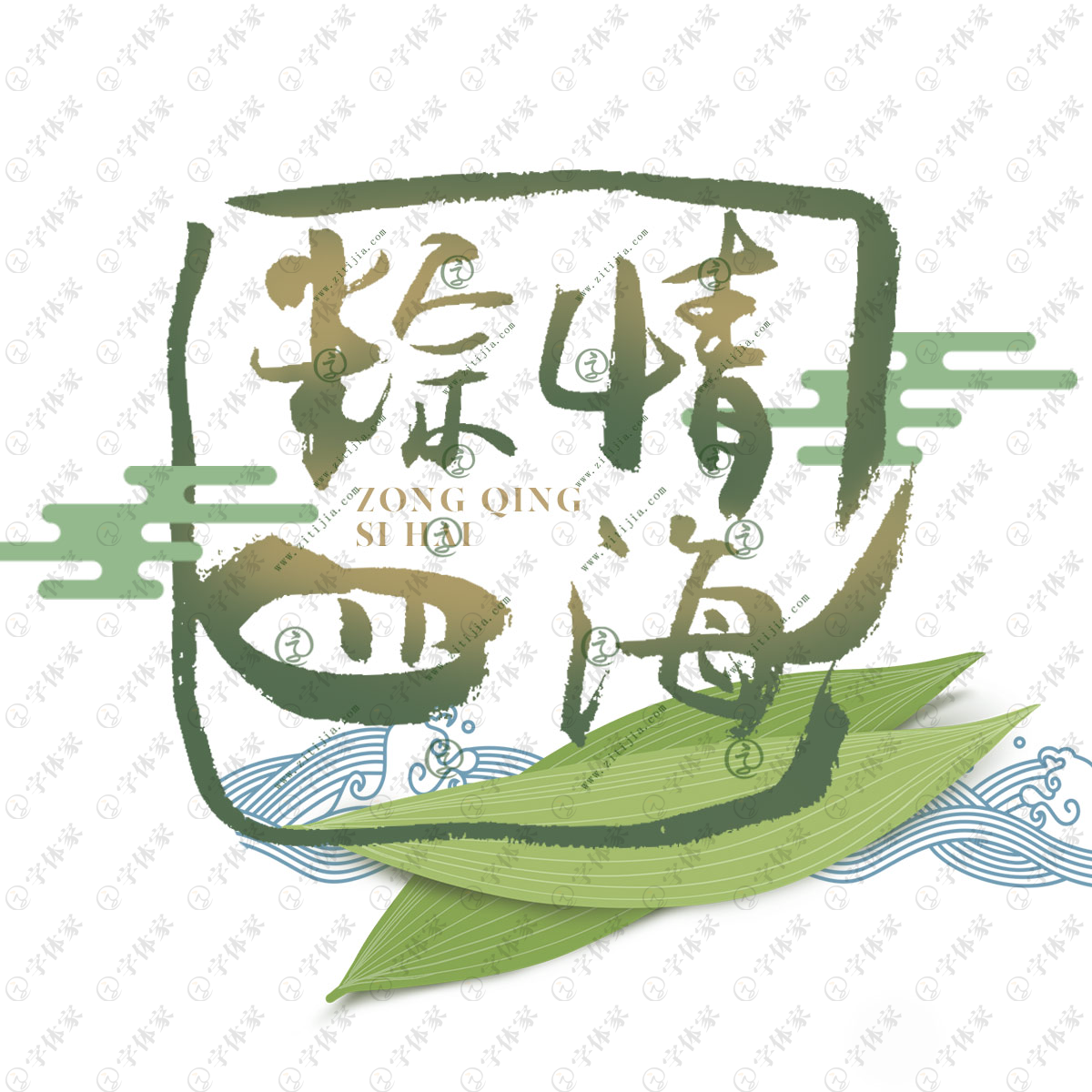
端午节,又称端阳节、龙舟节、重午节、天中节等,是集拜神祭祖、祈福辟邪、欢庆娱乐和饮食为一体的民俗大节。端午节源于自然天象崇拜,由上古时代祭龙演变而来。仲夏端午,苍龙七宿飞升于正南中央,处在全年最“中正”之位,正如《易经·乾卦》第五爻:“飞龙在天”。端午是“飞龙在天”吉祥日,龙及龙舟文化始终贯穿在端午节的传承历史中。
粽子,由粽叶包裹糯米蒸制而成的食品,是中国汉族传统节庆食物之一。粽子作为中国历史文化积淀最深厚的传统食品之一,传播亦甚远。端午食粽的风俗,千百年来,在中国盛行不衰,而且流传到朝鲜、日本及东南亚诸国。